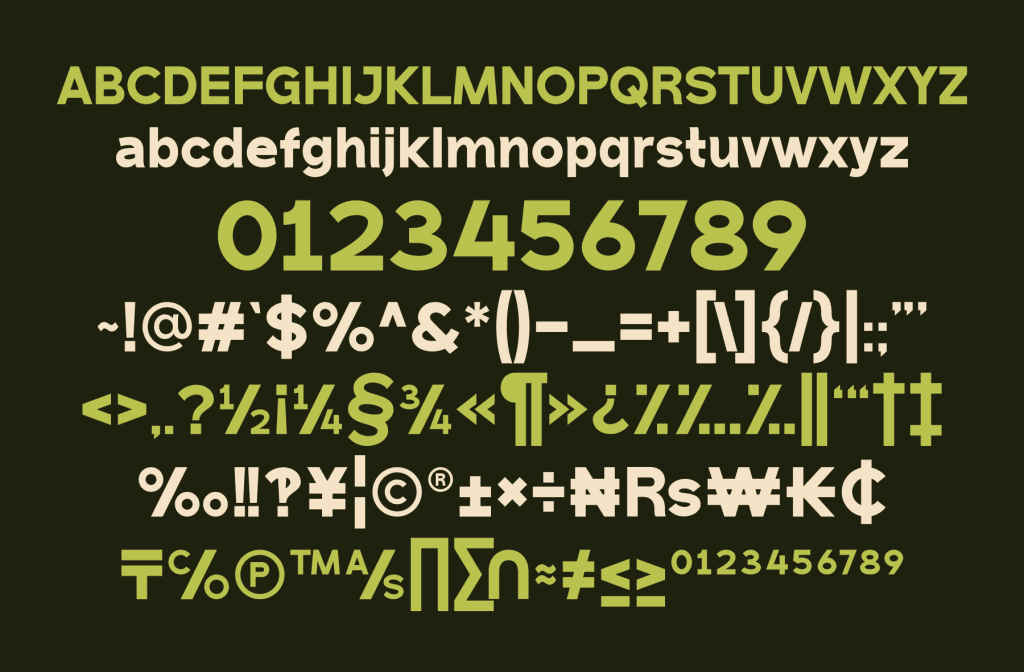
Phân loại: Hiện đại, tinh tế
Kiểu chữ: Sans-Serif
Font 1FTV Kalhen là một kiểu chữ hiện đại thuộc bộ font chữ 1FTV với phong cách thanh lịch và tinh tế. Các đường nét mềm mại kết hợp cùng sự tối giản mang lại vẻ đẹp nhẹ nhàng, trang nhã, rất phù hợp cho các dự án thiết kế cao cấp như thiệp mời, logo thương hiệu, hoặc các ấn phẩm quảng cáo mang tính chất thời trang và nghệ thuật. Font 1FTV Kalhen không chỉ giúp tôn lên tính thẩm mỹ cho các sản phẩm thiết kế mà còn tạo cảm giác sang trọng, thanh thoát, thu hút sự chú ý với sự đơn giản nhưng đầy tinh tế.
Bảng chữ cái và kí hiệu của Font 1FTV Kalhen